Indische Schriften
Auf dem indischen Subkontinent leben Dutzende eng verwandter Schriften nebeneinander — alle gehen letztlich auf die Brahmi-Schrift des 3. Jahrhunderts v. Chr. zurück. Jede Region hat ihre eigene Hand, und doch erkennt man die Familie.
Die indischen Schriften sind sogenannte Abugidas: jedes Zeichen steht grundsätzlich für eine Silbe aus Konsonant und einem inhärenten Vokal. Andere Vokale werden durch kleine Zusatzzeichen oberhalb, unterhalb oder seitlich des Buchstabens markiert — eine elegante, kompakte Lösung.
Aus der gemeinsamen Brahmi-Wurzel entwickelten sich Devanagari für Sanskrit und Hindi, Bengalisch, Gujarati, Tamil, Telugu, Kannada und viele weitere Schriften. Sie alle wirken auf den ersten Blick verschieden — und folgen doch demselben Bauplan.
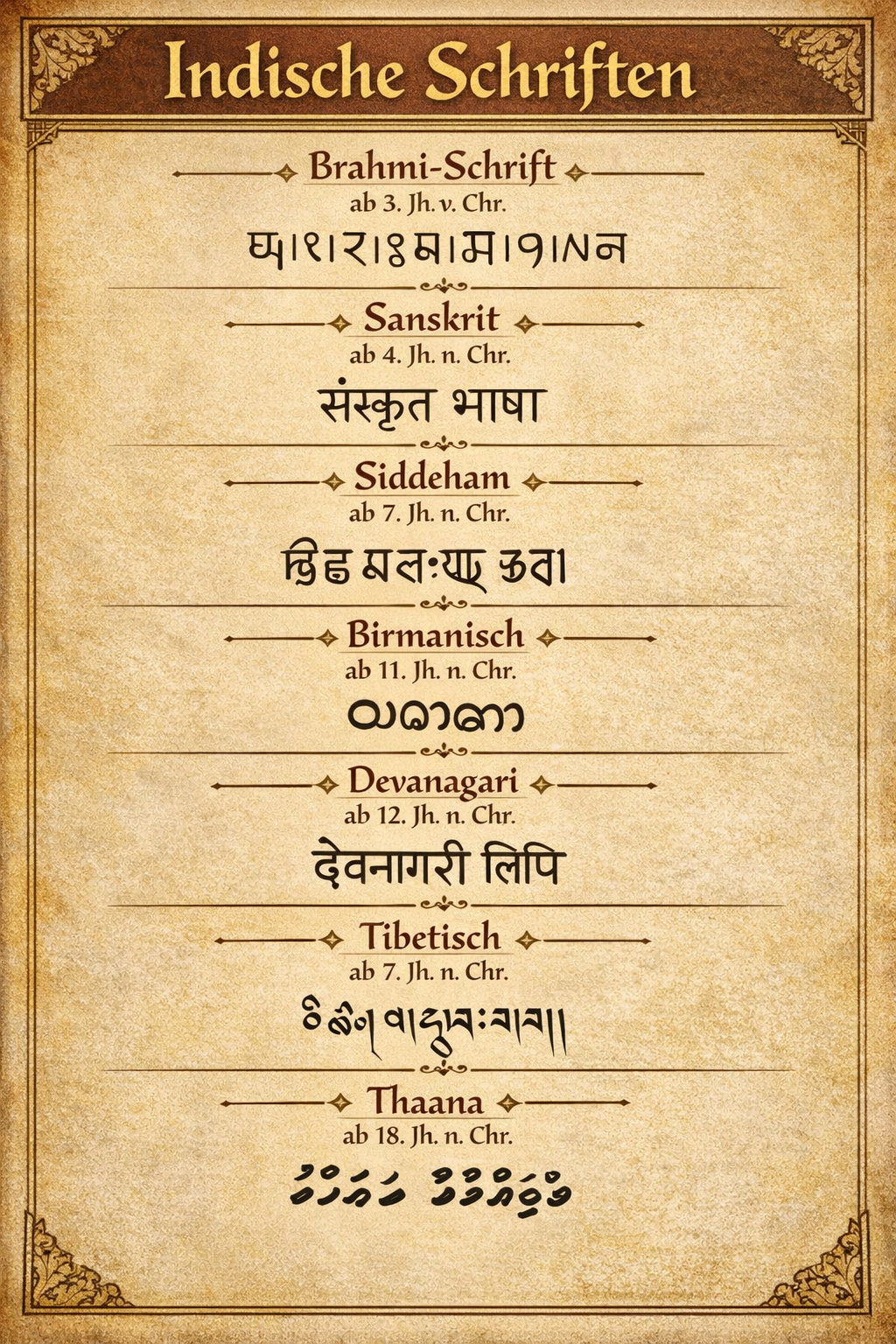
Eine Familie von Schriften
Von Brahmi zu Devanagari
Indische Schriftzeichen im Vergleich
Verwandte Hände, eigener Klang
Schon ein kurzer Blick zeigt, wie eng die indischen Schriften zusammengehören: dieselben Grundzüge, dieselbe Logik der Silbenzeichen — und doch eigene Rundungen, Bögen und Köpfe. Aus dieser Familie speist sich der größte Schriftraum Südasiens.